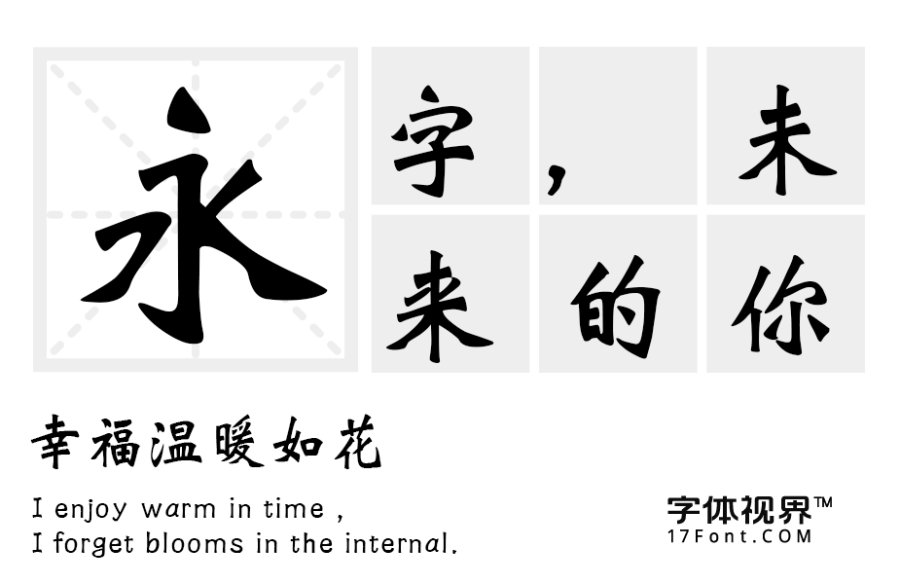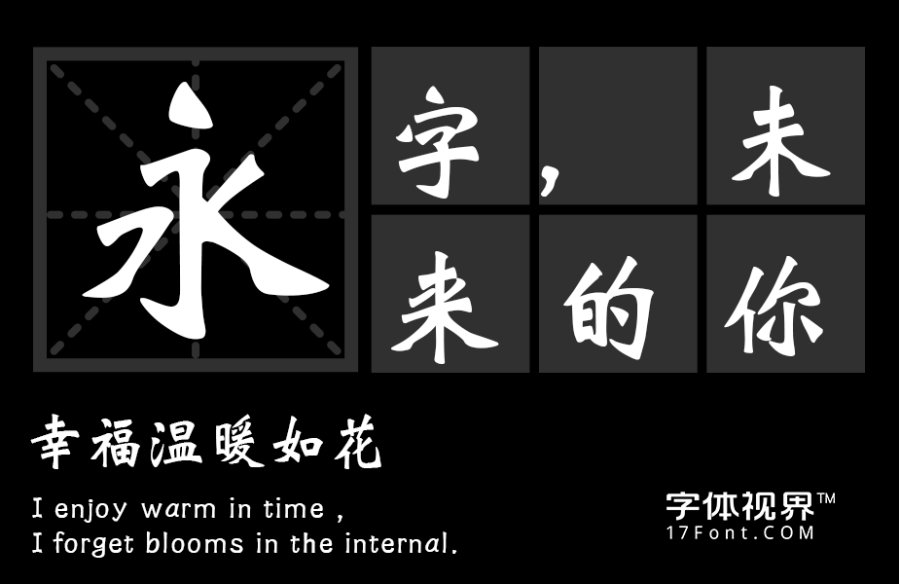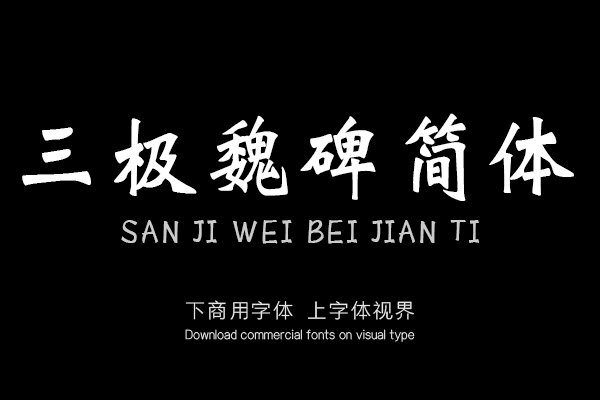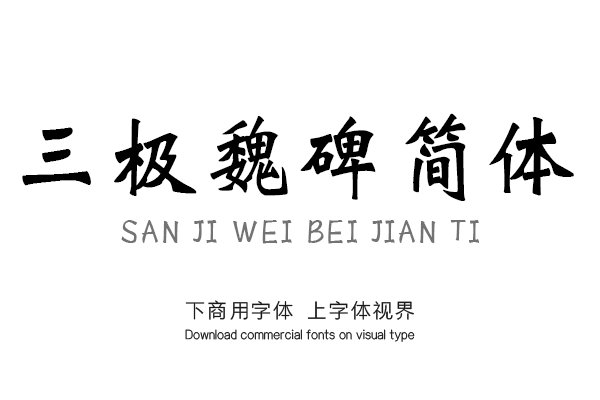
三极魏碑简体结构紧凑,笔意古拙,不避锋芒,中正庄重。充分体现了汉晋隶书与唐楷之变化字形遒劲有力。适用于各类便携式屏幕的系统嵌入字体,以及传统印刷媒介的标题与正文......购买须知:“下载服务费”与“字体VIP”所获得字体 仅用于个人非商用, 商用请联系付费授权。本字体为电脑用字,手机没有root权限不支持直接手机换字(手机如何root,请自行百度搜索教程)。购买前请先 了解清楚后再付款 ,字体为虚拟产品无法回收 一旦购买不支持退款。